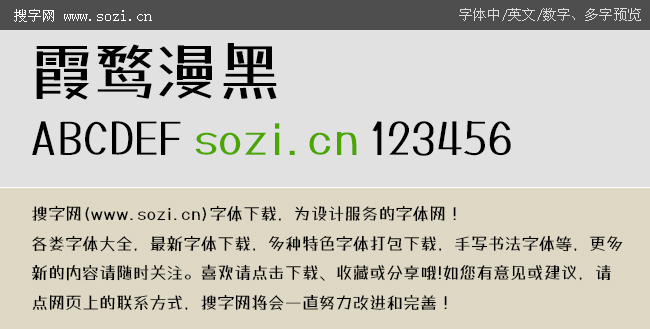
霞鶩漫黑
搜字網(wǎng)給大家提供一款霞鶩漫黑中文字體下載,霞鶩漫黑是一款由Tanugo手寫體衍生的開源中文字體。本字體是基于 たぬゴ角 改造的具有馬克筆書寫風格的中文字體,增補原字體中所含的繁體字對應(yīng)的簡體字及3500常用字。適用于海報設(shè)計、包裝設(shè)計、廣告設(shè)計等場景。